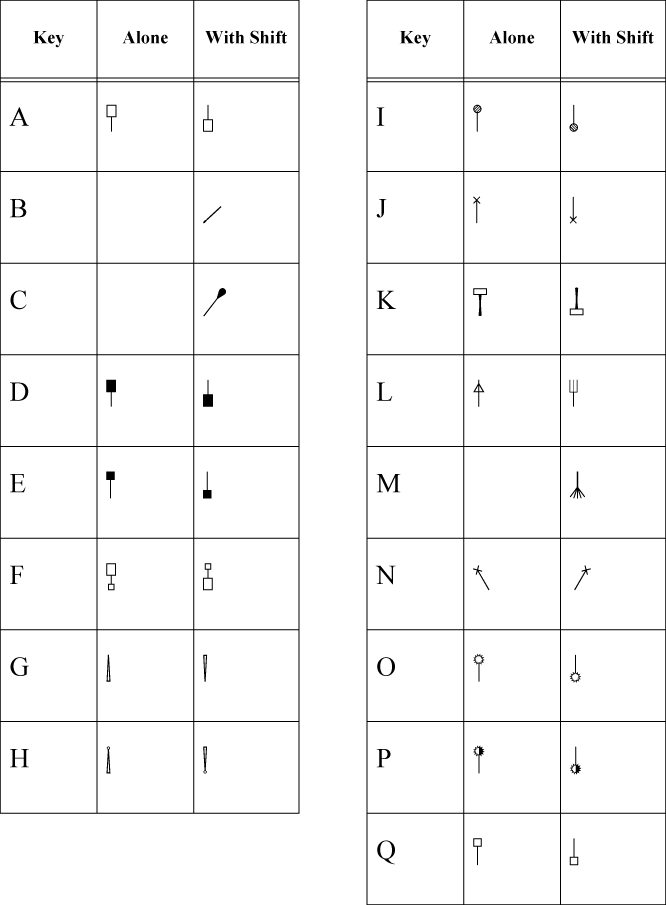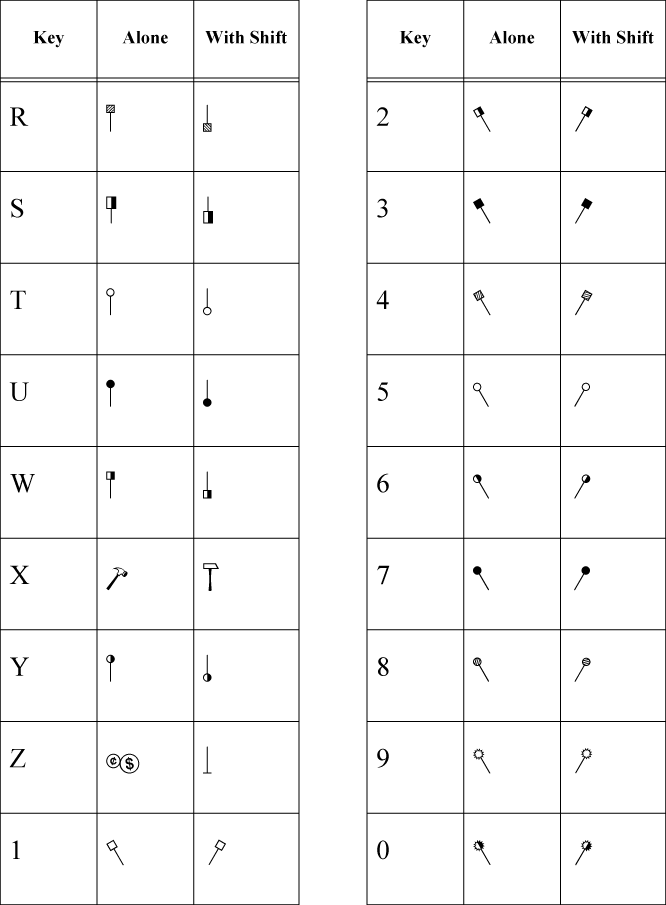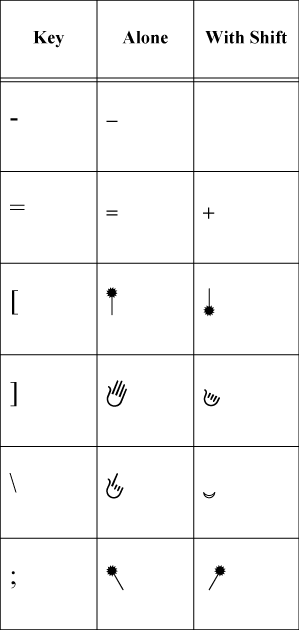
Font Finale Mallets
Il font Finale Mallets è composto di una serie di caratteri che rappresentano l'utilizzo di bacchette e mazzuoli per le percussioni, utili per creare la vostra simbologia. Ad esempio potreste utilizzare due caratteri come questi 7 per indicare all'esecutore di utilizzare due mazzuoli, uno leggero e uno più pesante, rispettivamente con le mani sinistra e destra.
Set di caratteri del font Finale Mallets